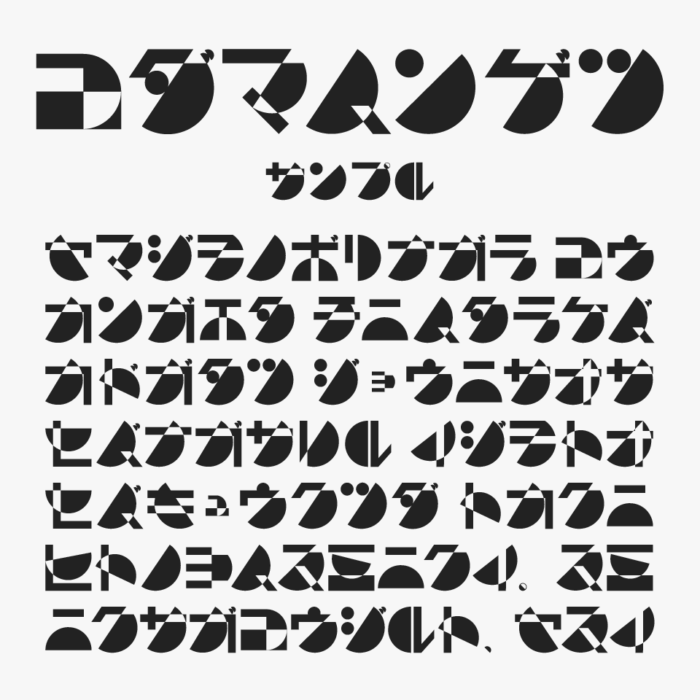
コダマハンゲツカタカナフォントは、正方形・三角形・半円などの幾何学的なパーツだけで文字を構成したコンセプチュアルなデザインカタカナフォントです。
面と形の組み合わせだけでカタカナを表現しており、文字というよりもアイコンやシンボルに近い印象になりつつ、きちんと文字として読める遊び心が満載なフォントです。
見ているだけでもとっても楽しめるステキなフォントです。